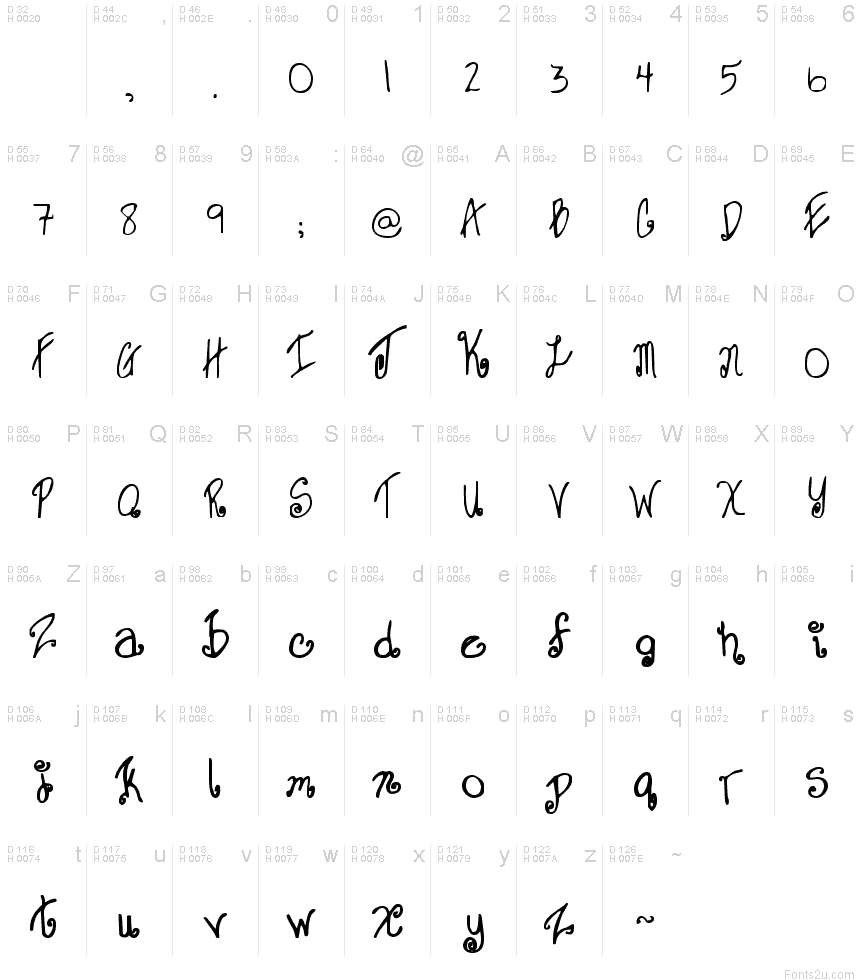
Sweet Janet to darmowy, ozdobny krój pisma o zabawnym, ręcznie rysowanym charakterze. Zapętlone spirale i długie, elastyczne pociągnięcia nadają literom luźny klimat popu lat 60., a zaokrąglone formy sprawiają, że całość jest przyjazna i przystępna.
Świetnie sprawdza się w przypadku opakowań butikowych, menu kawiarnianych, kartek okolicznościowych, plakatów eventowych oraz krótkich napisów w logotypach, którym darmowy font dodaje odrobinę życia. Wykorzystaj go do nagłówków, okładek lub dużych inicjałów – zawinięte końcówki oraz otwarte, kołyszące się kształty wykonują całą pracę stylizacyjną za Ciebie.